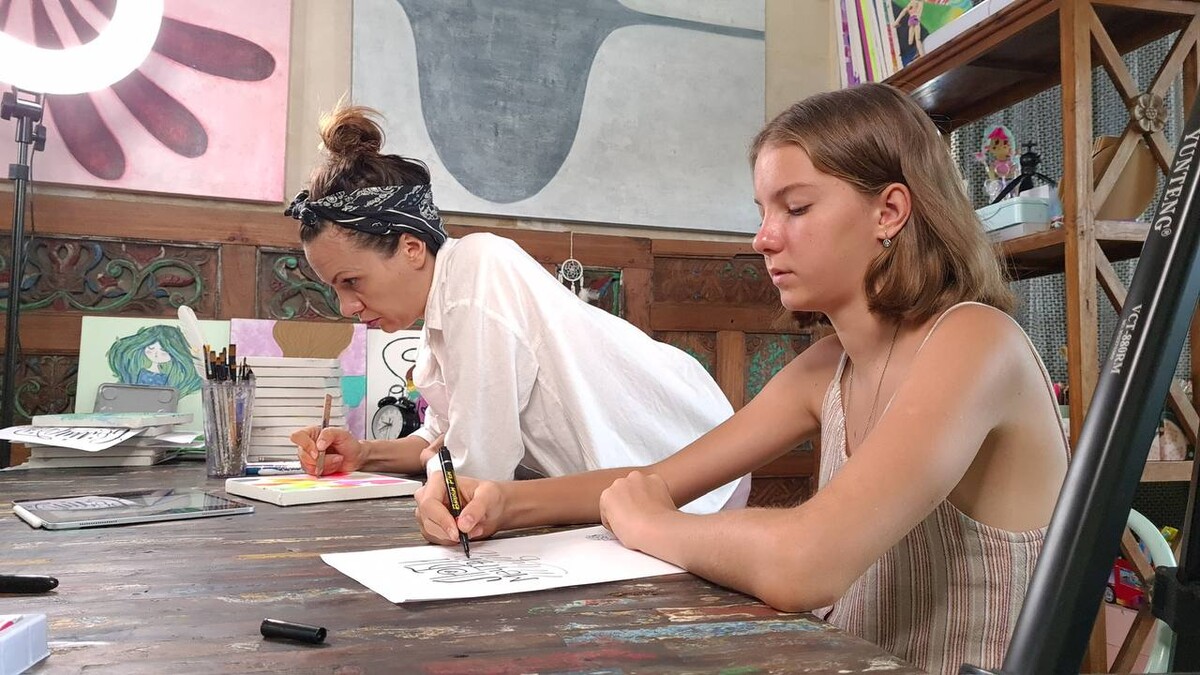
Часто ли вы ловили себя на том, что, стоя над склоненным ребенком, произносите как заклинание: «Ну постарайся! Просто будь внимательнее, пиши аккуратно»? В этот момент нам кажется, что почерк — это вопрос воли, прилежания и дисциплины. Мы верим: если ребенок приложит чуть больше усилий, буквы перестанут плясать, а грязь исчезнет. Однако правда заключается в том, что «старайся» — это одна из самых деструктивных фраз в процессе обучения письму.
Как эксперт, я часто вижу одну и ту же картину: ребенок честно пытается, его лицо напряжено, пальцы сжимают ручку до белых костяшек, но результат становится только хуже. И дело здесь не в лени. Проблема в том, что старание без отточенной техники не равно навыку. Более того, избыточное усилие превращается в физическое напряжение, которое буквально блокирует мозг и руку.
Когда старание становится преградой
Письмо — это сложнейший психофизиологический процесс. Это не естественное умение, как ходьба, которому мы учимся сами. Письмо — это искусственный навык, который требует определенной готовности тела и мозга. Сегодня дети приходят в школу физически менее подготовленными, чем тридцать-сорок лет назад: они меньше бегают, меньше завязывают шнурки и тренируют мелкую моторику. Их тело не чувствует легкости.
Когда мы требуем от такого неподготовленного ребенка «стараться», происходит подмена понятий. Вместо того чтобы держать внимание на форме буквы или строке, ребенок начинает «держать напряжение». Он сжимает ладонь, поднимает плечо, задерживает дыхание. Вся энергия уходит в зажатую руку. Через пять минут наступает истощение. Ребенок искренне говорит: «Я устал», а мы видим в этом каприз. Но это не характер — это физика. Ресурс мозга потрачен на борьбу с собственным телом, а не на красоту письма.
Письмо как спорт: почему техника важнее воли
Представьте себе пловца, который хочет пересечь бассейн быстрее всех, но не умеет правильно грести. Сколько бы он ни «старался», как бы сильно ни бил руками по воде, без техники он лишь быстрее выбьется из сил. Письмо — это точно такой же спорт. Здесь есть свой «вдох и выдох», свое направление движения и своя техника.
Буква — это не просто картинка, которую нужно скопировать. Буква — это след движения. Если направление этого движения выбрано неверно (например, пресловутые овалы, которые дети часто пишут по часовой стрелке вместо «против»), письмо ломается. Оно становится медленным, корявым и неразборчивым. Требовать от ребенка аккуратности в такой ситуации — всё равно что просить стрелка попасть в цель из лука, который он даже не умеет правильно держать. Мы не должны призывать «быть аккуратным», мы должны дать инструмент, который сделает письмо естественным.
Путь к успеху: правильная последовательность
В современной школе на обучение письму отводится всего 12 недель вместо прежних четырех лет. В таких условиях педагоги часто сразу переходят к объему, пропуская важнейшие этапы. Но навык не складывается из отдельных уроков «через силу». У него есть своя непоколебимая логика развития, которую мы называем траекторией успеха.
1. Интерес. Это топливо. Без «хочу» не будет «могу». Сначала мы активируем желание, превращая каллиграфию в игру, чтобы ребенку было просто любопытно прикоснуться к бумаге.
2. Движение. Мы учим руку быть легкой. Если рука расслаблена, мысль течет быстрее. Это фундамент уверенности в себе.
3. Техника. Только когда рука «почувствовала» инструмент, мы объясняем правила: где начало буквы, куда вести линию, как соединять элементы. Это дает ясность.
4. Объем. И только в самом конце, когда техника понятна и не вызывает боли, мы наращиваем количество написанного.
Если нарушить эту последовательность и начать с объема (тех самых бесконечных прописей), мы получим только слезы и отвращение к учебе. Ребенок начнет бояться ошибки, а красная паста в тетради станет для него символом безысходности. Наша задача как взрослых — перевести это «тяжело» в «легко».
Чтобы помочь вам и вашему ребенку пройти этот путь без стресса и бесконечных переписываний, мы подготовили встречу, где покажем, как запустить этот процесс правильно.
От принуждения к пониманию
Когда мы убираем из своего лексикона деструктивное «старайся» и заменяем его на «посмотри, как это движение делает букву легкой», климат в семье меняется. Мы перестаем быть надзирателями и становимся партнерами.
Помните, что письмо — это не только про оценки. Это про самооценку ребенка. Когда у него начинает получаться легко, когда рука слушается, а буквы ложатся ровно без титанических усилий, он чувствует себя победителем. Это ощущение — «я могу» — переносится на все остальные предметы.
Давайте не будем требовать от детей невозможного старания в поломанной системе. Давайте дадим им правильную технику, верную последовательность и нашу поддержку. Письмо может и должно быть таким же естественным, как дыхание. И начинается этот путь не с дисциплины, а с нашего понимания того, как на самом деле работает навык